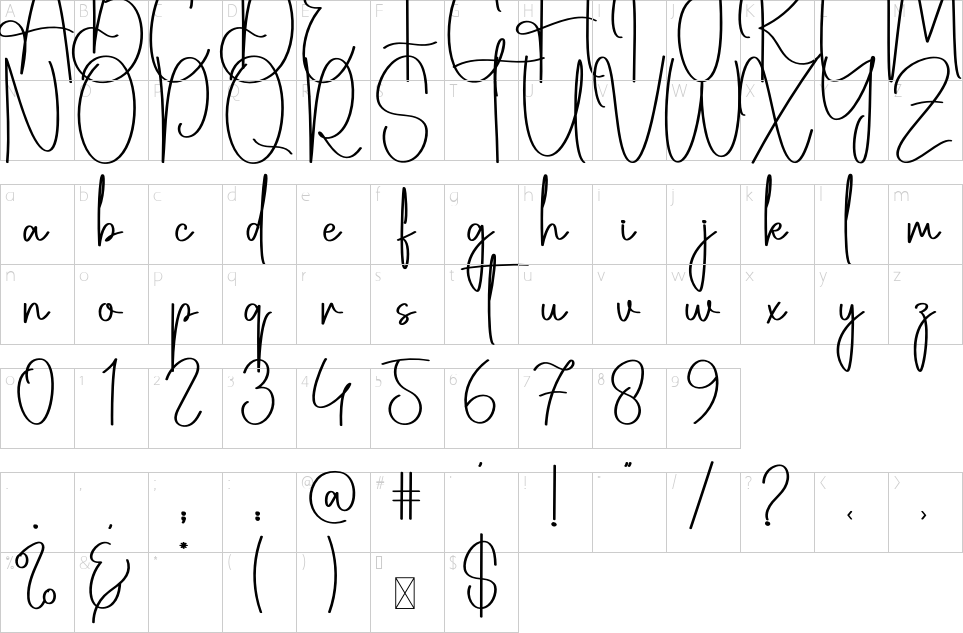
Descubra Mistyping, uma fonte originalmente criada pelo designer scratchones. Esta fonte foi projetada para oferecer um toque de casualidade e frescor na sua próxima publicação ou projeto. Mistyping é adequada para designers gráficos, web designers, e qualquer pessoa que busca um novo olhar para suas criações. Ela foi projetada para Windows e Mac, garantindo uma experiência de uso fluida. Envolvente e natural, Mistyping carrega consigo uma certa dose de irreverência que certamente pode adicionar um toque especial a seu trabalho. Com uma baixa demanda de downloads, Mistyping oferece uma fonte única e exclusiva sem comprometer o seu valor. Não deixe de experimentar Mistyping para uma experiência de design única.